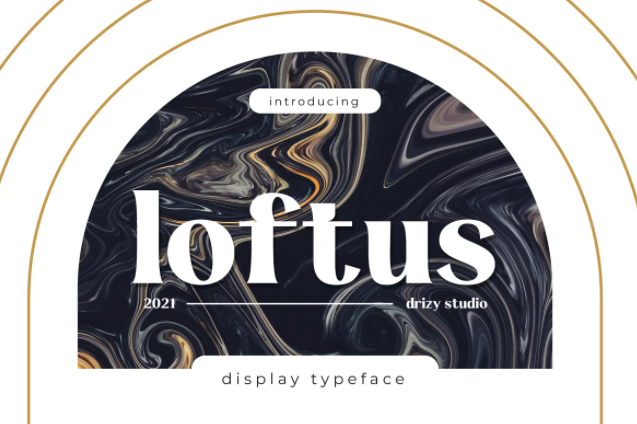
Шрифт Loftus - это особый шрифт для современного уникального дизайна.
Предлагает все основные стили, которые вам понадобятся для успешного проекта.
Особенности Loftus:
Прописные и строчные цифры и знаки препинания Альтернативы и многоязычность